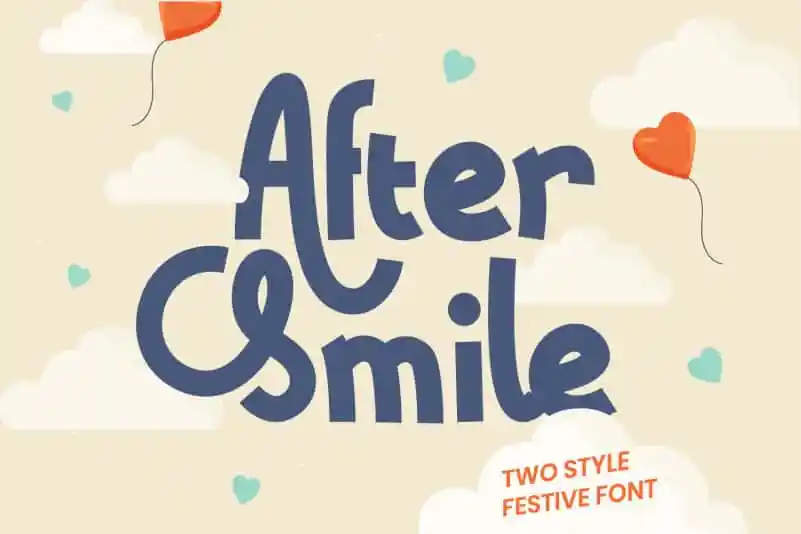
After Smile Display Font – Download Grátis
A fonte ‘After Smile Display Font’ é uma opção criativa para quem busca um toque alegre em seus projetos digitais. Desenvolvida pelo designer Heloyud, esta é uma fonte sans-serif de efeito grande que traz consigo uma pitada de suavidade e simplicidade. Especificamente projetada para agregar um toque alegre e doce às suas ideias de design, ‘After Smile Display Font’ será uma excelente escolha para quem deseja dar um sorriso extra em qualquer projeto, seja ele impresso ou digital. A simplicidade elegante e o ar delicado desta fonte torna-a versátil o suficiente para ser usada em designs variados, desde logotipos até materiais de marketing. Que tal incorporar alegria e bom humor em seus projetos com esta fonte?
Designer: Heloyud